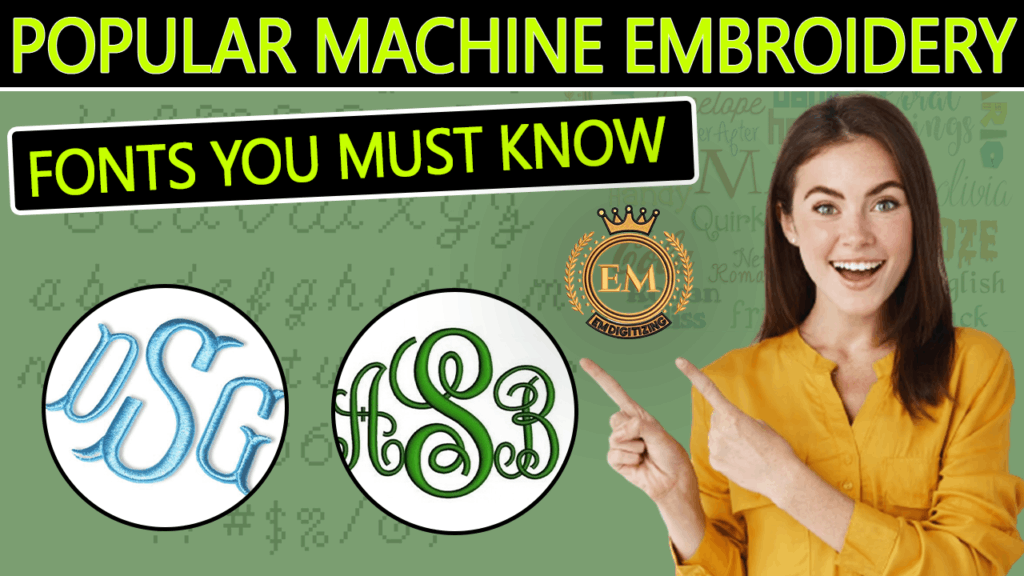
Polices de machine à broder populaires que vous devez connaître
Dans cet article, nous explorerons certaines polices de machines à broder populaires que vous devriez connaître. Nous fournirons une brève description de chaque style de police et de ses meilleures applications pour vous aider à choisir la police parfaite pour votre prochain projet de broderie..
Popular Embroidery Machine Fonts You Must Know
Polices de machine à broder populaires que vous devez connaître
La broderie est une forme d'art pratiquée depuis des siècles, et avec l'avènement des machines à broder, il est devenu encore plus accessible et personnalisable. L'une des principales caractéristiques d'une machine à broder est sa capacité à utiliser différentes polices pour créer des motifs uniques et personnalisés.. Les polices de machines à broder sont disponibles dans une variété de styles, du classique au moderne, et peut être utilisé pour créer des monogrammes, logos, et d'autres modèles.
1. Scénario:
Script
Scénario
Les polices script se caractérisent par leurs lignes élégantes et fluides, ce qui en fait un choix populaire pour les monogrammes et les motifs de mariage.
2. Bloc:
Block
Bloc
Les polices de bloc sont audacieuses et simples, ce qui en fait un excellent choix pour les logos et autres designs qui nécessitent une lisibilité.
3. Serif:
Serif
Les polices Serif ont de petites lignes ou des fioritures à la fin de leurs traits, ce qui en fait un choix populaire pour les occasions formelles motifs de broderie.
4. Sans Serif:
Sans Serif
Les polices Sans Serif n'ont pas de petites lignes ou de fioritures, leur donnant un look plus moderne et épuré.
5. Contour:
Outline
Contour
Les polices de contour sont créées en cousant le contour de chaque lettre, laissant l'intérieur vide. Ils constituent un choix populaire pour les logos et les motifs de broderie qui nécessitent un look plus minimaliste..
6. 3D Puff:
3D Puff
3Les polices D Puff sont créées en utilisant un support en mousse sous les points, créant un effet de relief qui donne au design un aspect tridimensionnel.
7. Exécuter le point:
Run Stitch
Exécuter le point
Les polices Run Stitch sont créées en cousant une seule ligne pour créer chaque lettre., leur donnant un look simple et élégant.
8. Plumetis:
Satin Stitch
Plumetis
Les polices Satin Stitch sont créées en cousant une série de points rapprochés pour remplir l'intérieur de chaque lettre., leur donnant un aspect lisse et brillant.
9. Point de haricot:
Bean Stitch
Point de haricot
Les polices Bean Stitch sont créées en utilisant un point zigzag serré pour créer chaque lettre., leur donnant un look fantaisiste et ludique.
10. Point de croix:
Cross Stitch
Point de croix
Les polices de point de croix sont créées en cousant une série de points en forme de X pour créer chaque lettre., leur donnant un look classique et traditionnel.
11. Ancien:
Vintage
Ancien
Les polices vintage sont conçues pour donner l’impression qu’elles ont été créées à une époque révolue, ce qui en fait un choix populaire pour les designs rétro ou nostalgiques.
12. Graffiti:
Graffiti
Les polices graffiti s'inspirent du street art et ont un look audacieux et audacieux, ce qui en fait un choix populaire pour les designs urbains et modernes.
13. Cousu: Police manuscrite:
Stitched Handwritten Font
Cousu: Police manuscrite
Le cousu est un produit populaire Machine à broder police qui imite l'apparence d'une écriture manuscrite. Ce style de police se caractérise par son lettrage cursif aux lignes légèrement irrégulières et ondulées qui créent un aspect naturel et organique.. Stitched est une police polyvalente qui peut être utilisée dans une variété de projets de broderie, surtout ceux qui nécessitent une touche personnalisée et artisanale.
14. Cursive au point de croix:
Cross Stitch Cursive
Cursive au point de croix
Cross Stitch Cursive est une police de machine à broder qui imite l'apparence d'une écriture cursive créée avec des points de croix.. Ce style de police se caractérise par l'utilisation d'une série de points en forme de X pour créer chaque lettre., donnant au texte un aspect classique et traditionnel qui rappelle les travaux d'aiguille à l'ancienne.
15. Bonjour:
Good Morning
Bonjour
Un bonjour est un message populaire Machine à broder police qui se caractérise par son caractère fluide, lettrage de style script. Cette police a une allure moderne et contemporaine qui est parfaite pour un large éventail de projets de broderie., des vêtements à la décoration intérieure. Good Morning est une police relativement nouvelle qui a rapidement gagné en popularité parmi les amateurs de broderie grâce à son aspect élégant et polyvalent..